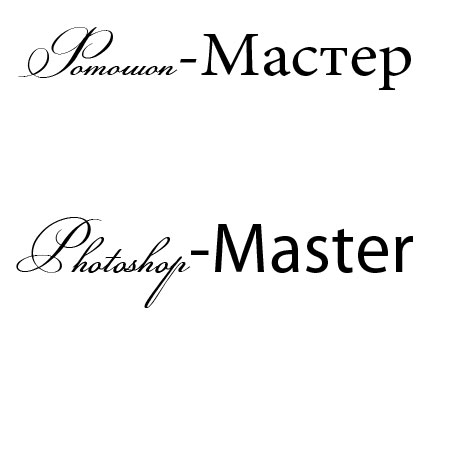
А подскажите, как его настроить, он у меня только курсивом, а вот как написано слово Мастер такого нет...
Та да свадебние класно получаются
Шикарный шрифт! Очень подходит для подписи свадебных фото!
ммм.. красивый ^^